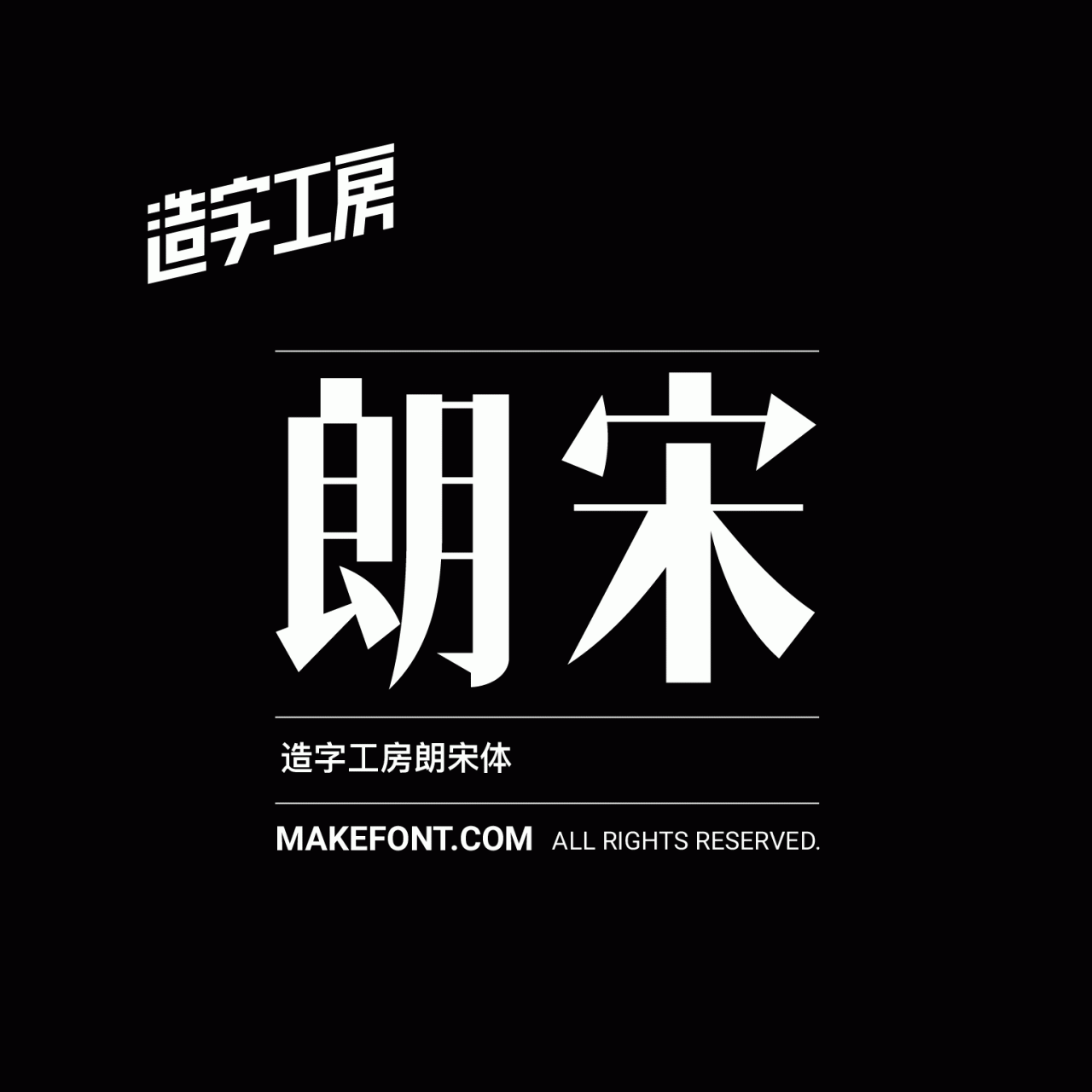
造字工房朗宋常规体设计说明
造字工房朗宋字体源于上世纪五、六十年代宣传标语街头海报等书写字形,结合现代设计语言和市场需求而精心设计的一款中文字体。整体字形笔画简洁有力,笔画粗细关系明确,使得字形空间结构自然平衡,整套字体庄重严谨,沉稳厚重,具有良好时代气息的同时,完全符合现代的审美识别需求。此款字体适用于文字标题、广告设计等等视觉环境,有着极强的应用空间。